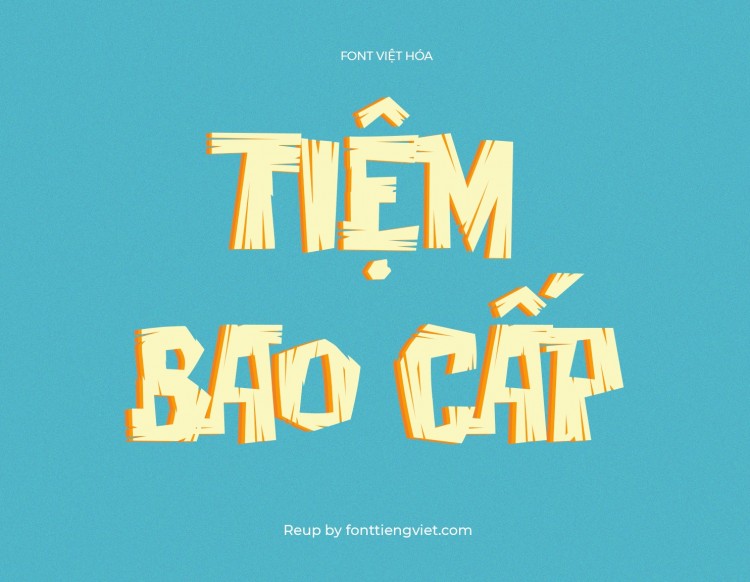
Font việt hóa MTD Creaky Frank
Giới thiệu về Font việt hóa MTD Creaky Frank
Trong thế giới thiết kế đồ họa, việc lựa chọn một bộ font chữ phù hợp đóng vai trò quyết định đến sự thành công của một tác phẩm nghệ thuật. Font việt hóa MTD Creaky Frank là một trong những lựa chọn hàng đầu cho những ai đang tìm kiếm sự phá cách và độc đáo. Được biết đến với phong cách thiết kế mang hơi hướng cổ điển nhưng không kém phần hiện đại, bộ Font Miễn Phí này giúp các nhà thiết kế dễ dàng truyền tải thông điệp một cách mạnh mẽ. Đặc biệt, phiên bản được MTD việt hóa đã giải quyết triệt để vấn đề lỗi hiển thị dấu tiếng Việt, giúp người dùng tại Việt Nam có thể sử dụng mượt mà trên các phần mềm thiết kế phổ biến hiện nay.
Tại sao nên chọn Font việt hóa MTD Creaky Frank?
Lý do đầu tiên khiến Font việt hóa MTD Creaky Frank trở nên phổ biến chính là sự tỉ mỉ trong từng đường nét. Bộ font này sở hữu những nét vẽ có phần thô mộc, góc cạnh, gợi liên tưởng đến các bảng hiệu vẽ tay của những thập niên trước. Đối với các bạn học sinh và giáo viên, đây là công cụ tuyệt vời để trang trí bài giảng điện tử hoặc làm báo tường thêm phần sinh động. Sự linh hoạt của nó cho phép ứng dụng trong nhiều lĩnh vực khác nhau như thiết kế logo, làm tiêu đề video hay thậm chí là in ấn trên áo thun và bao bì sản phẩm. Việc sử dụng font việt hóa giúp nội dung tiếng Việt trở nên chuyên nghiệp và thẩm mỹ hơn bao giờ hết.
Đặc điểm nổi bật của bộ font chữ này
Font việt hóa MTD Creaky Frank không chỉ dừng lại ở việc đẹp mắt mà còn sở hữu tính ứng dụng cực cao. Với cấu trúc ký tự rõ ràng, người xem có thể dễ dàng đọc được nội dung ngay cả khi font được sử dụng ở kích thước nhỏ. Điều này rất quan trọng trong việc trình bày các tài liệu học tập hoặc các poster quảng cáo ngoài trời.
Phong cách thiết kế độc bản
Mỗi ký tự trong bộ font này đều được chăm chút để tạo nên một tổng thể hài hòa. Những đường cong nhẹ nhàng kết hợp với các nét gạch chân mạnh mẽ tạo nên một nhịp điệu thị giác thú vị. Font việt hóa MTD Creaky Frank mang đến cảm giác thân thiện, gần gũi nhưng vẫn giữ được sự tinh tế cần thiết cho các dự án sáng tạo chuyên nghiệp.
Việc sở hữu một bộ font chữ chất lượng như Font việt hóa MTD Creaky Frank sẽ giúp bạn nâng tầm thẩm mỹ cho mọi dự án cá nhân. Để đạt được hiệu quả tốt nhất, bạn nên kết hợp font này với các tông màu trầm hoặc màu tương phản mạnh để làm nổi bật thông điệp chính. Hãy luôn ghi nhớ rằng một thiết kế đẹp bắt đầu từ những lựa chọn nhỏ nhất nhưng tinh tế nhất. Đừng ngần ngại trải nghiệm ngay để thấy sự khác biệt mà nó mang lại cho tác phẩm của bạn. Bạn có thể tìm kiếm thêm nhiều lựa chọn tại Font Miễn Phí, Font Việt Hóa, Font việt hóa MTD Creaky Frank để làm phong phú thêm thư viện sáng tạo của mình ngay hôm nay.